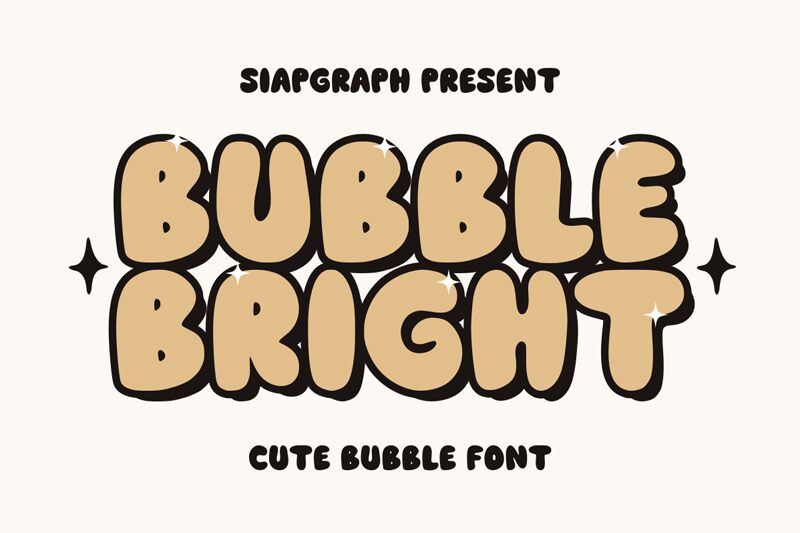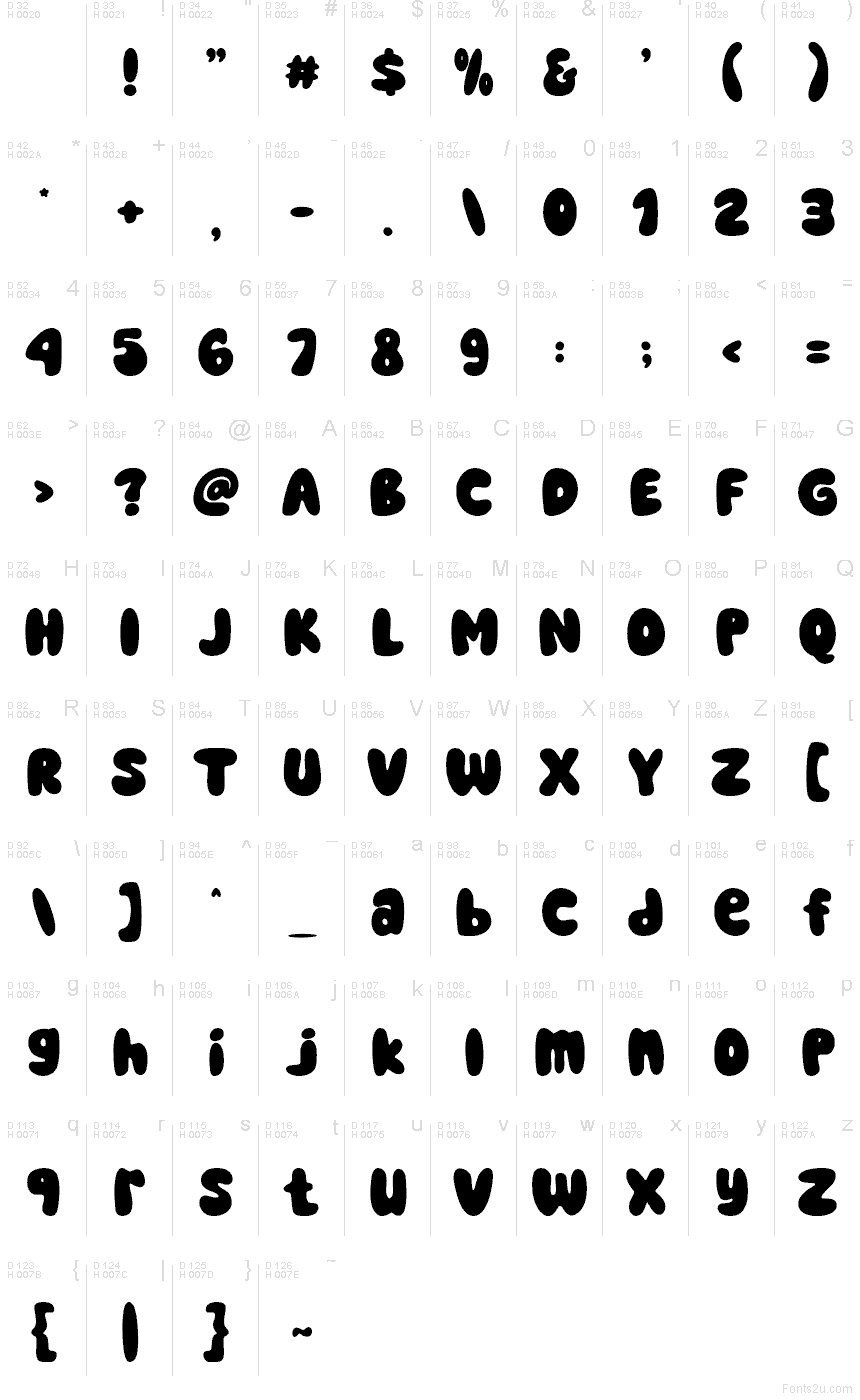
Bubble Bright Regular
Bubble Bright od SIAPGRAPH STUDIO je bezplatné kreslené písmo postavené na nafúknutých, vzpriamených tvaroch a hlbokých zaoblených rezoch, vďaka ktorým pôsobia písmená ako z mäkkého vinylu. Táto objemná silueta dodáva dizajnu hravosť bez toho, aby pôsobila neporiadne; každý znak má kompaktnú a výraznú masu, ktorá pripomína skôr poskakujúce tvary než bežné titulkové písmo.
Narodeninové pozvánky, detské obaly, branding hračiek, školské plagáty a veselé grafiky na sociálne siete – tam všetkým sa toto písmo skvele hodí. Široká, zaoblená konštrukcia dodáva krátkym slovám priateľský náboj, takže je ideálne pre nálepky alebo párty nadpisy, kde záleží viac na výraznom, bublinkovom obryse než na jemných detailoch.